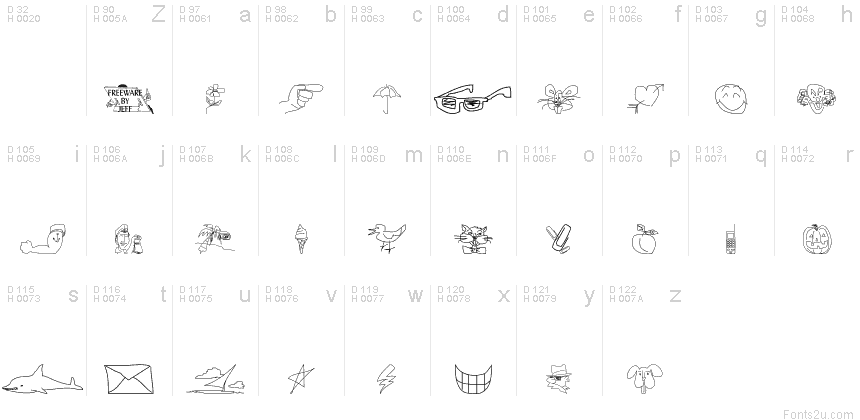
Screen Scrawls JL di Jeffrey N. Levine è un font dingbat in stile cartoon gratuito, caratterizzato da quell'aspetto libero e improvvisato tipico dei bozzetti fatti con il pennarello. Il set pittorico punta su disegni a contorno semplice e soggetti giocosi – un ombrello, una zucca, un coniglio – rendendo l'atmosfera generale leggera, stagionale e un po' birichina, piuttosto che troppo raffinata.
Questo font gratuito è perfetto per flyer di feste, poster di Halloween, dispense scolastiche, album di ritagli e biglietti d'auguri in cui poche icone abbozzate possono definire subito il tema. Funziona bene anche per illustrazioni spot, titoletti e piccoli stacchi decorativi, dato che i disegni sembrano scarabocchi casuali inseriti direttamente nel layout.
Mappa dei caratteri di Screen Scrawls JL: Latino di base, pagina 1